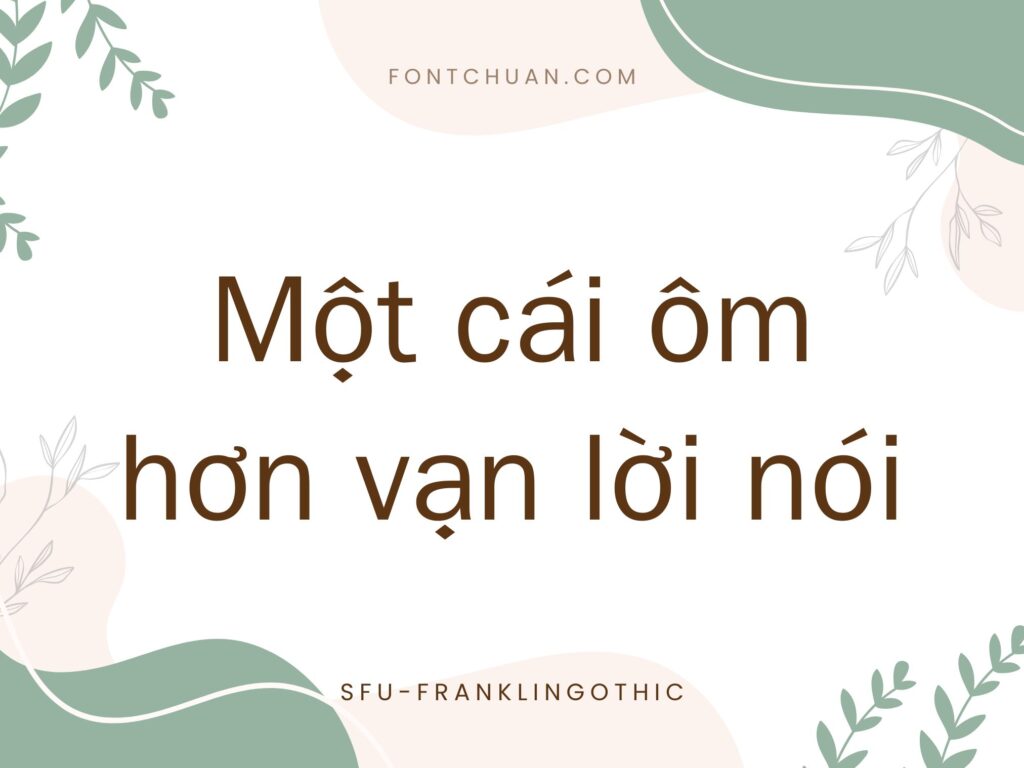
Franklin Gothic là một kiểu chữ sans-serif thuộc nhóm grotesque, được thiết kế bởi Morris Fuller Benton và phát hành bởi American Type Founders (ATF) vào năm 1902. Tên gọi “Franklin” được cho là nhằm tôn vinh Benjamin Franklin, một trong những người sáng lập Hoa Kỳ và cũng là một thợ in nổi tiếng. Font này được sưu tầm và đăng bởi thành viên của Font Chuẩn.
Về mặt thiết kế, Franklin Gothic nổi bật với các đường nét đậm, chắc chắn và cấu trúc chữ rõ ràng, tạo cảm giác mạnh mẽ và đáng tin cậy. Với đặc điểm này, font không chỉ phù hợp làm Font logo cho các thương hiệu cần sự vững chắc và hiện đại, mà còn được đánh giá cao khi ứng dụng như một Font chữ quảng cáo, giúp thu hút ánh nhìn trong các ấn phẩm truyền thông và thương mại. Franklin Gothic còn có thể được biến tấu thành Font chữ Tết để thiết kế thiệp, poster hay banner chúc mừng năm mới, mang không khí lễ hội. Đồng thời, kiểu chữ này cũng lý tưởng làm Font ngày Nhà giáo Việt Nam, dùng trong các thiệp chúc mừng, ấn phẩm kỷ niệm hay banner tôn vinh giáo viên, vừa trang trọng vừa dễ đọc. Các ngành nghề như quảng cáo, giáo dục, bất động sản và công nghệ đều có thể tận dụng Franklin Gothic để tạo dấu ấn đặc biệt và linh hoạt trong truyền thông.